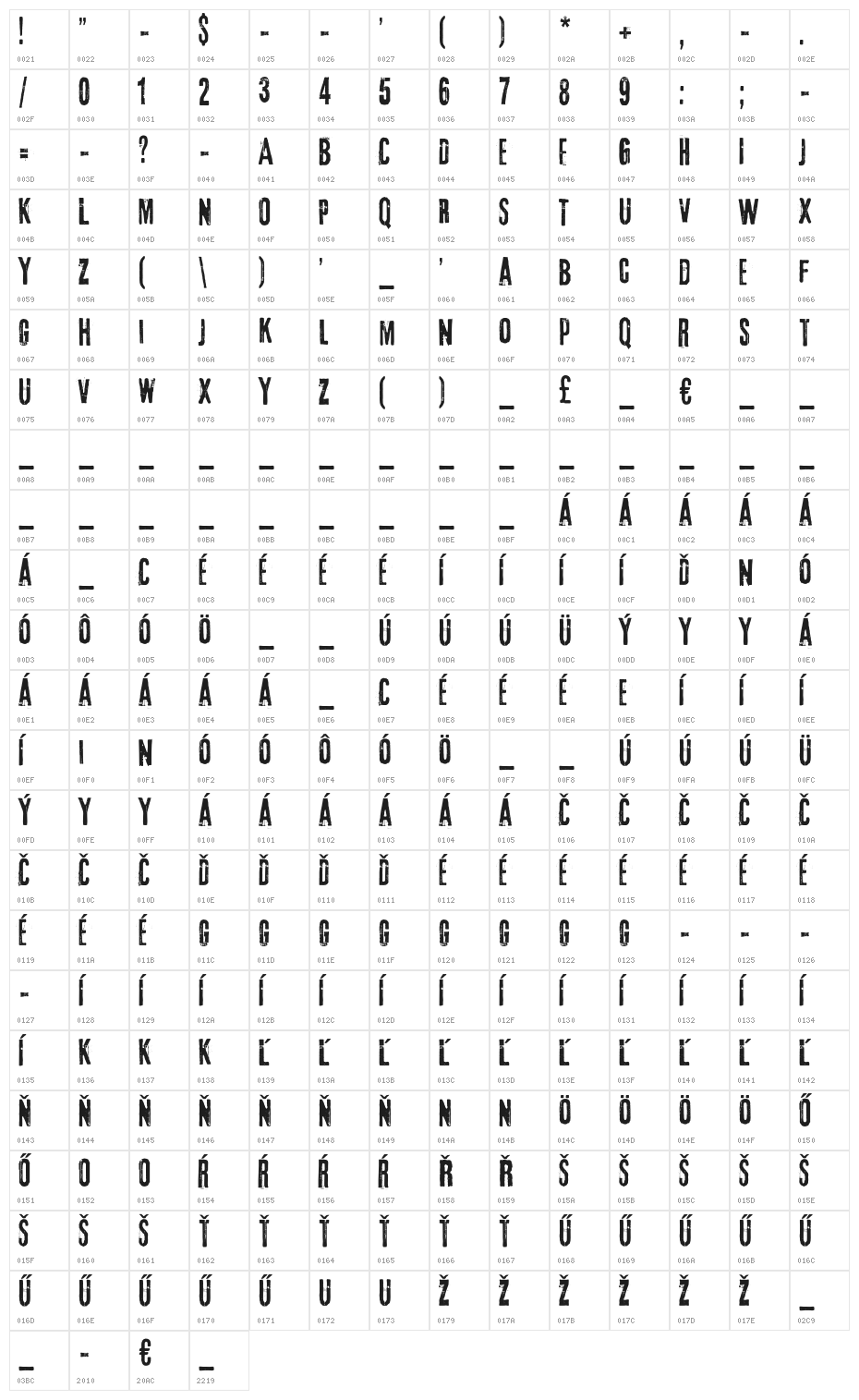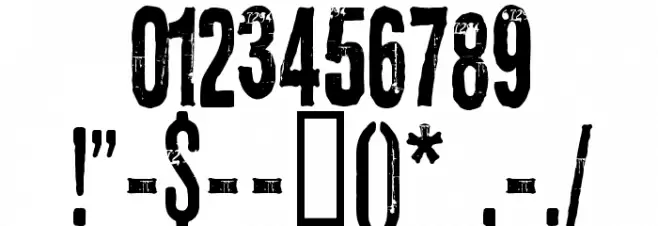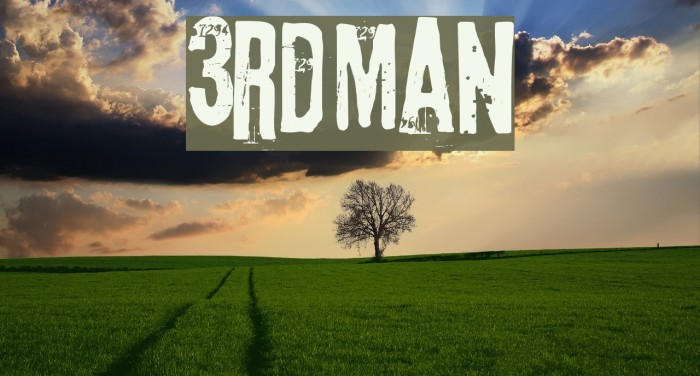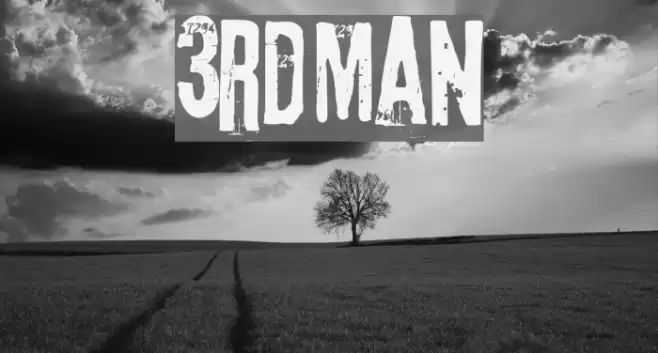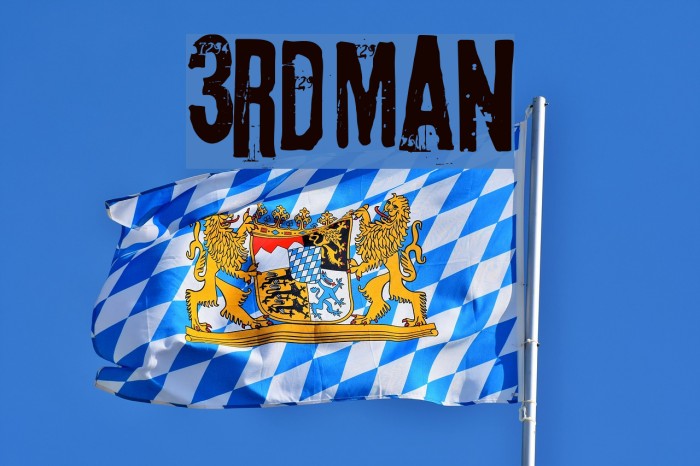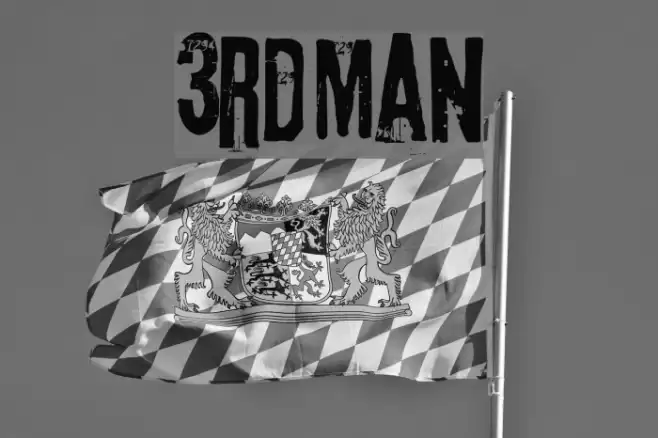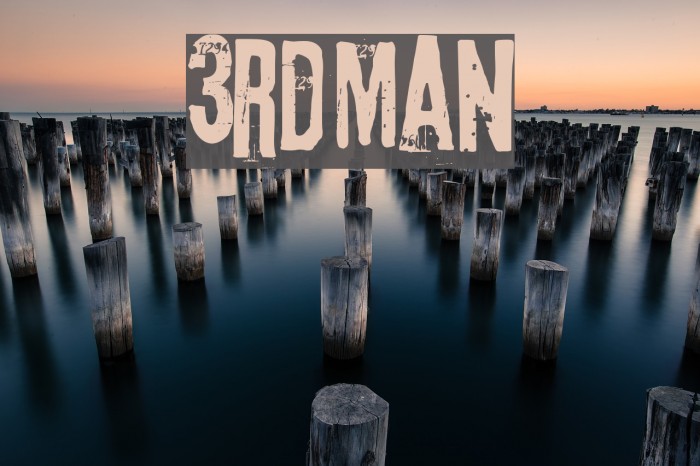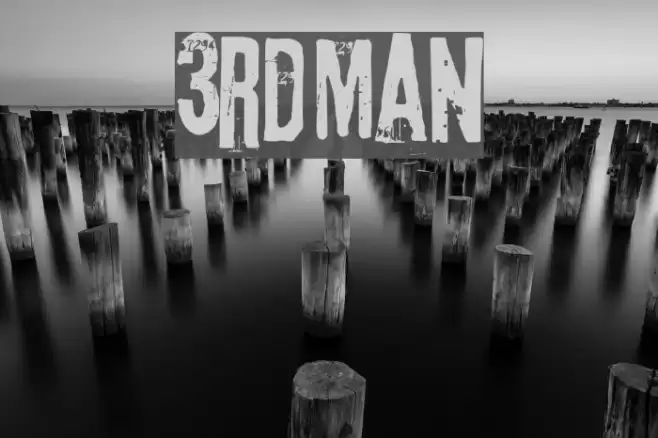
3rdMan Font
| Estilo general | Vintage |
| Proyectos propuestos | Ideal for posters, album covers, branding projects, and any design requiring a strong, vintage aesthetic. |